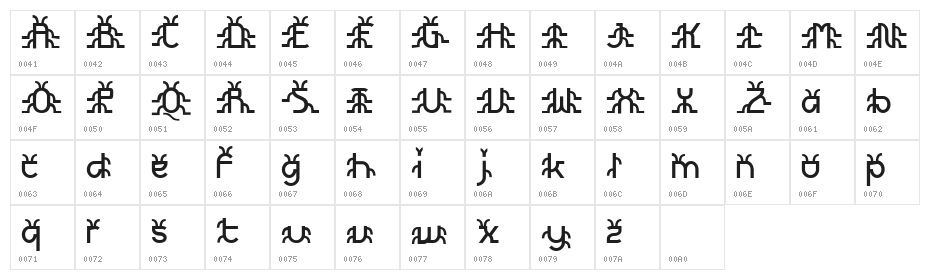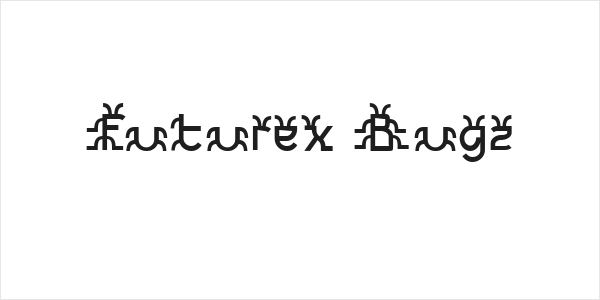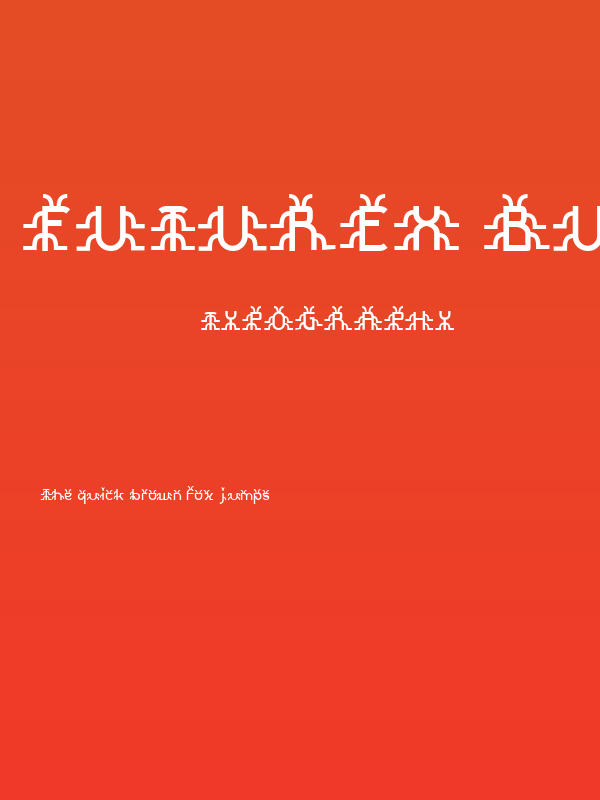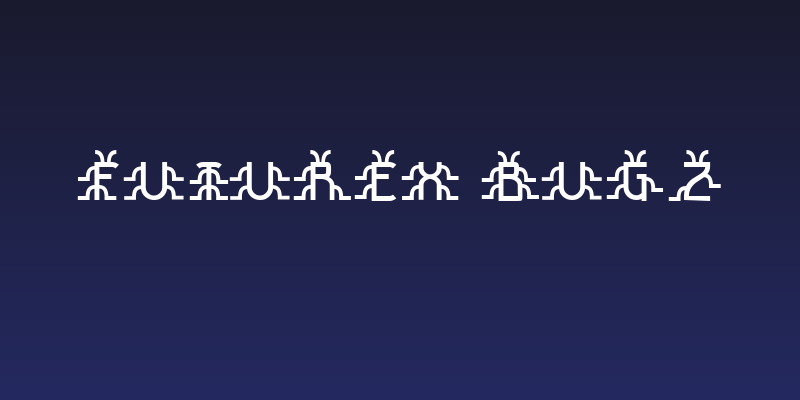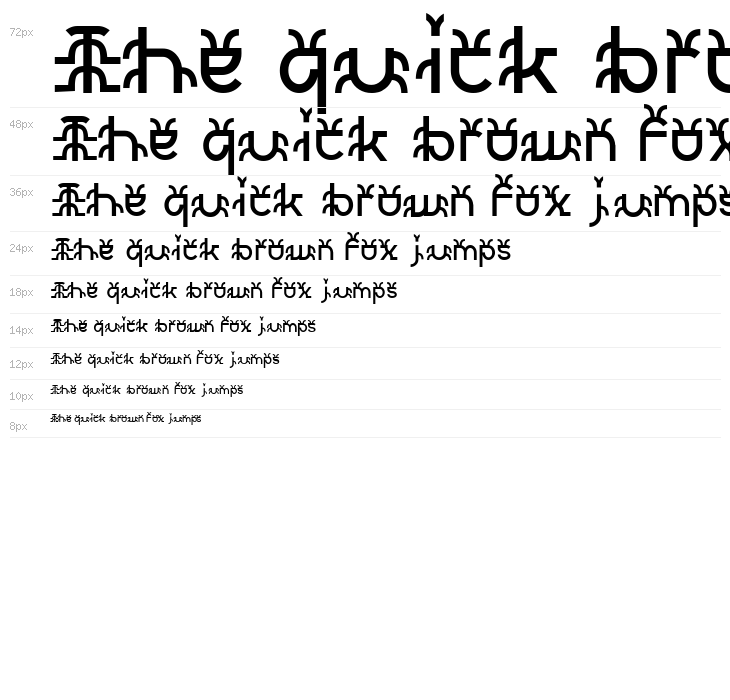
Futurex Bugz Font
| Stil general | Futuristic, Avant-garde |
| Caz de utilizare | Logos, Posters, Creative Branding |
| Proiecte propuse | Ideal for sci-fi themed designs, futuristic branding, creative posters, and unique logo designs. |